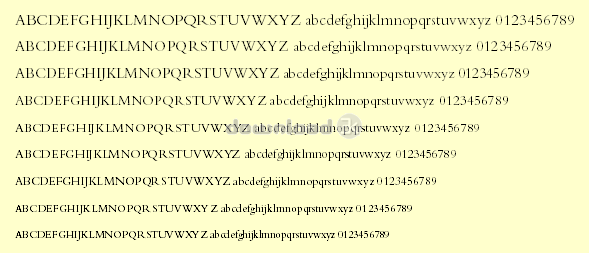
"Serif book font, calligraphic feel."
Rubicon Polices Bentley. Post-scriptum. Comme Bembo. Police Serif livre avec une sensation calligraphique, pour les livres et de longs passages de texte sur papier de bonne qualité. Recommandé taille 12 points. Précis et laissé entendre. Métriques de police de contrepartie, la norme configurer Windows-1251 de caractère, paires de crénage. Qualité dimpression professionnelle pour jet dencre, laser, typographe à 3500 dpi. Contient 1 police dessai, envoyer 12 $ pour recevoir tous les 3 polices de production.Exigences: Older versions of Mac OS require Adobe Type Manager.